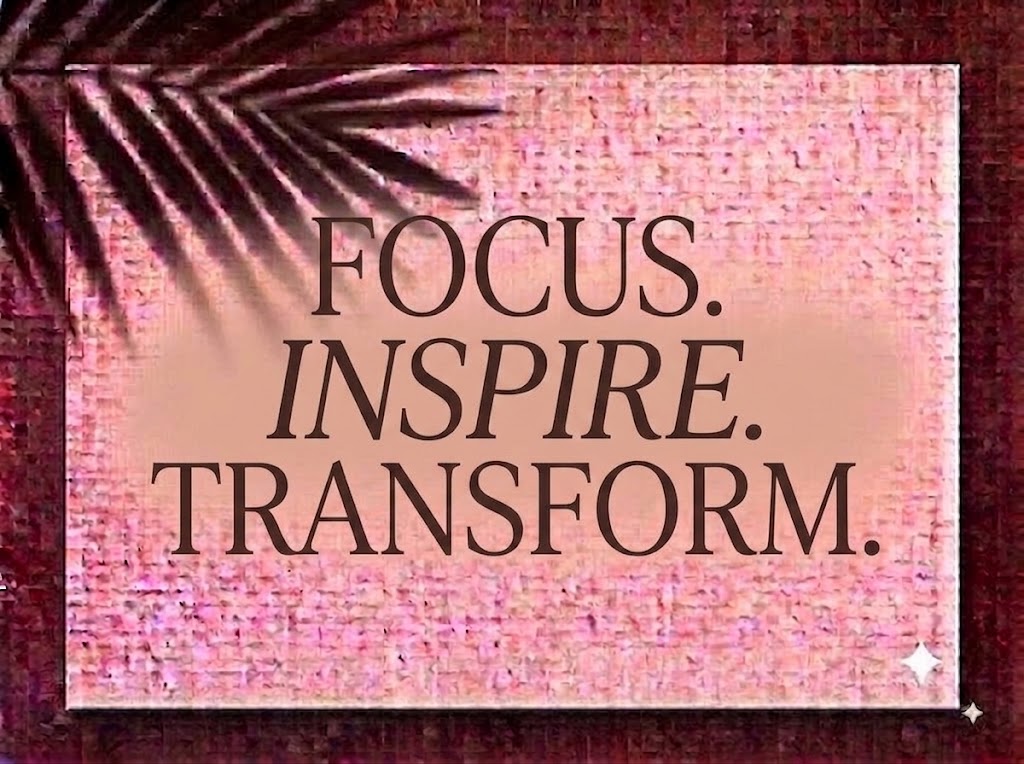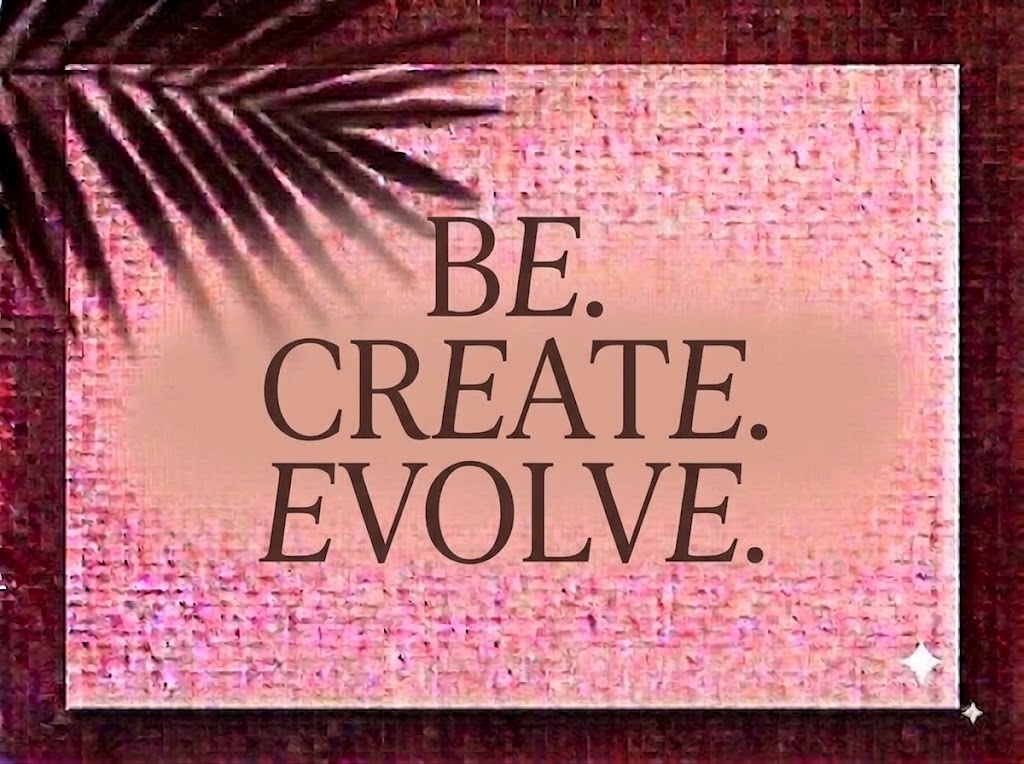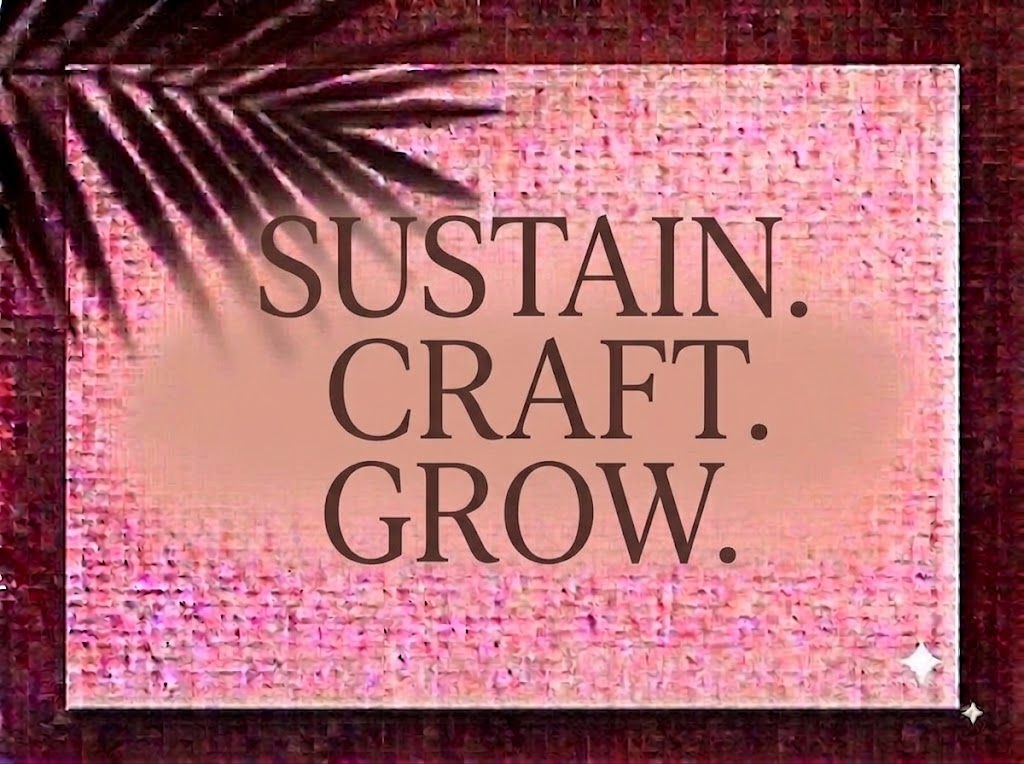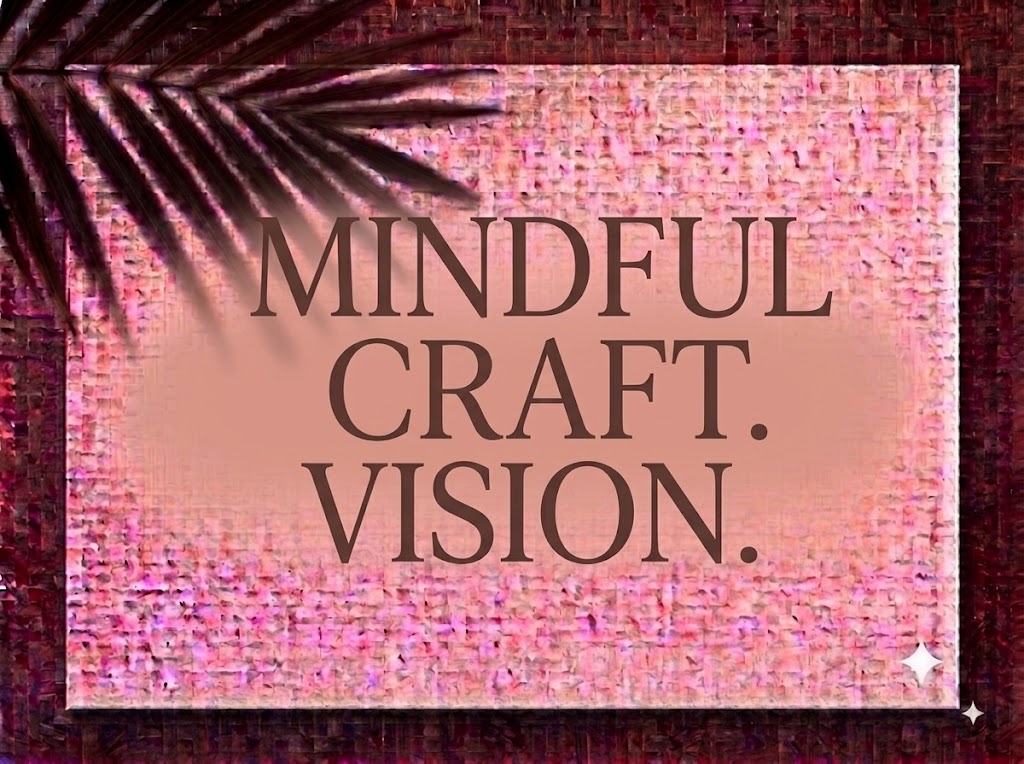
Trong nghệ thuật thiết kế đồ họa cao cấp và xuất bản tạp chí thời trang (Editorial), những bộ phông chữ hiển thị có chân (Display Serif) với độ tương phản sắc sảo luôn giữ vị trí độc tôn trong việc kiến tạo cảm xúc kiêu sa, đài các. Một dòng tiêu đề tinh tế không chỉ truyền tải thông điệp ngắn gọn mà còn lập tức nâng tầm thẩm mỹ và định vị đẳng cấp cho toàn bộ bộ nhận diện thương hiệu.
Nếu bạn đang tìm kiếm một phông chữ Serif thanh thoát, sở hữu các đường nét uốn vát quý phái để làm logo spa, bìa lookbook, bao bì nước hoa hay tiêu đề video ngắn phong cách Aesthetic, font 1FTV VIP Astetes chính là sự lựa chọn không thể bỏ qua.
Giới thiệu về font 1FTV VIP Astetes
Font 1FTV VIP Astetes là bộ chữ hiển thị có chân (display serif) mang phong cách tân cổ điển hiện đại, nổi bật với sự giao thoa hài hòa giữa cấu trúc thanh mảnh và các đường cong biến điệu nghệ thuật:
Đặc điểm nổi bật của ngôn ngữ thiết kế VIP Astetes
Sức hút thị giác của font 1FTV VIP Astetes đến từ tỷ lệ chữ thon dài cùng sự trau chuốt tỉ mỉ trong từng đường nét:
Tương phản thanh đậm kịch tính (High Contrast): Sự đối lập rõ rệt giữa cột nét dọc thanh thoát và các đường cong ngang mỏng manh mang đến vẻ đẹp mong manh, kiều diễm, gợi liên tưởng trực tiếp đến những thương hiệu thời trang haute couture hàng đầu thế giới.
Chân chữ Serif tinh tế & Nét uốn mềm mại: Phần chân chữ và các điểm kết thúc nét (terminals) được vuốt nhọn hoặc uốn cong nhẹ nhàng ở các ký tự như
t,f,r,a,c,y, tạo nên nhịp điệu đọc uyển chuyển và đầy tính nghệ thuật. -
Đồng bộ chữ hoa và chữ thường: Bộ chữ in hoa kiên cố, chuẩn mực kết hợp hoàn hảo cùng dàn chữ thường mềm mại, giúp nhà thiết kế dễ dàng phân tầng thông tin và sắp xếp bố cục tiêu đề đa dạng.
Tối ưu hiển thị và dấu tiếng Việt từ 1FTV
Để phông chữ vận hành mượt mà trên cả nền tảng Windows lẫn macOS, phiên bản này đã được xử lý kỹ lưỡng về mặt thông số nội tại:
Khoảng cách ký tự (Kerning): Khoảng hở giữa các chữ cái được tính toán cân đối, đảm bảo các nét chữ thanh mảnh khi đứng cạnh nhau không bị dính nét hay tạo cảm giác ngột ngạt.
Bản Việt hóa chuẩn chỉnh: Hệ thống dấu thanh tiếng Việt (sắc, huyền, hỏi, ngã, nặng, mũ, móc) từ fonttiengviet được tạo hình thanh thoát, đặt đúng trọng tâm thị giác, giúp các câu chữ tiếng Việt có dấu giữ trọn vẹn nét sang trọng mà không bị rối mắt.
Hệ thống ký tự đồng bộ: Tích hợp trọn vẹn dãy số từ 0-9 phom dáng đứng thanh lịch cùng đầy đủ các ký hiệu toán học và dấu câu cơ bản.
Đánh giá hiển thị thực tế
Khả năng hiển thị của phông chữ được tối ưu linh hoạt theo nhiều kích cỡ:
Kích thước nhỏ (12pt – 24pt): Cấu trúc chữ rành mạch và khoảng hở nội tại thoáng giúp các câu ngắn, trích dẫn hay dãy số vẫn hiển thị rõ ràng trên màn hình di động.
Kích thước lớn (36pt – 72pt): Đây là đất diễn lý tưởng nhất để 1FTV VIP Astetes phô diễn toàn bộ vẻ đẹp kiêu kỳ, quý phái và độ sắc sảo của các đường nét Serif thanh mảnh cho các dòng headline chính.
Ứng dụng trong thiết kế đồ họa và sản xuất video
Sở hữu nét cá tính thanh lịch và đậm chất thời trang cao cấp, font 1FTV VIP Astetes mở ra không gian ứng dụng phong phú:
Video ngắn (TikTok, Reels, Shorts): Dáng chữ Serif thanh thoát hiển thị rất đẹp mắt trên khung hình đứng tỷ lệ 9:16. Cực kỳ ăn nhập với các video vlog thời trang, review mỹ phẩm, trang sức, spa thẩm mỹ hay video phong cách sống lãng mạn.
Ảnh thu nhỏ YouTube (Thumbnail): Lựa chọn tuyệt vời cho các kênh làm nội dung về làm đẹp, thời trang, podcast tâm sự, âm nhạc acoustic hay review đồ hiệu nhờ diện mạo đẳng cấp.
Nhận diện thương hiệu Luxury: Hoàn hảo để thiết kế logo dạng chữ cho thẩm mỹ viện, viện áo cưới, cửa hàng trang sức, nhãn hiệu nước hoa, nến thơm hay thời trang may đo thiết kế.
Ấn phẩm Editorial & Thiệp cưới: Rất thích hợp làm bìa tạp chí, lookbook thời trang, thiệp mời tiệc cưới cao cấp, menu nhà hàng Fine Dining hay brochure triển lãm nghệ thuật.